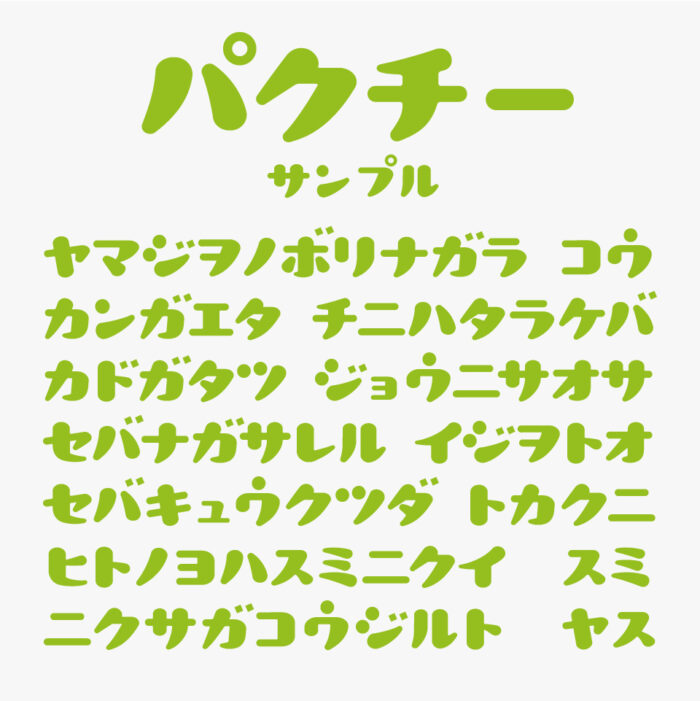
パクチー
パクチーフォントは、グレイグラフィックスさんがtwitter上で配布しているカタカナのみのプクッとした丸みがあるカワイイフォントになります。
ぷくっとした膨らみがとっても印象的なデザインで、フォント名が「パクチー」というのも愛らしいポイントです。親しみやすくレトロな雰囲気を持ち合わせているので、レトロなロゴやキャッチコピーなどとの相性がとっても良いフォントです。
収録文字は、カタカナのみとなっています。